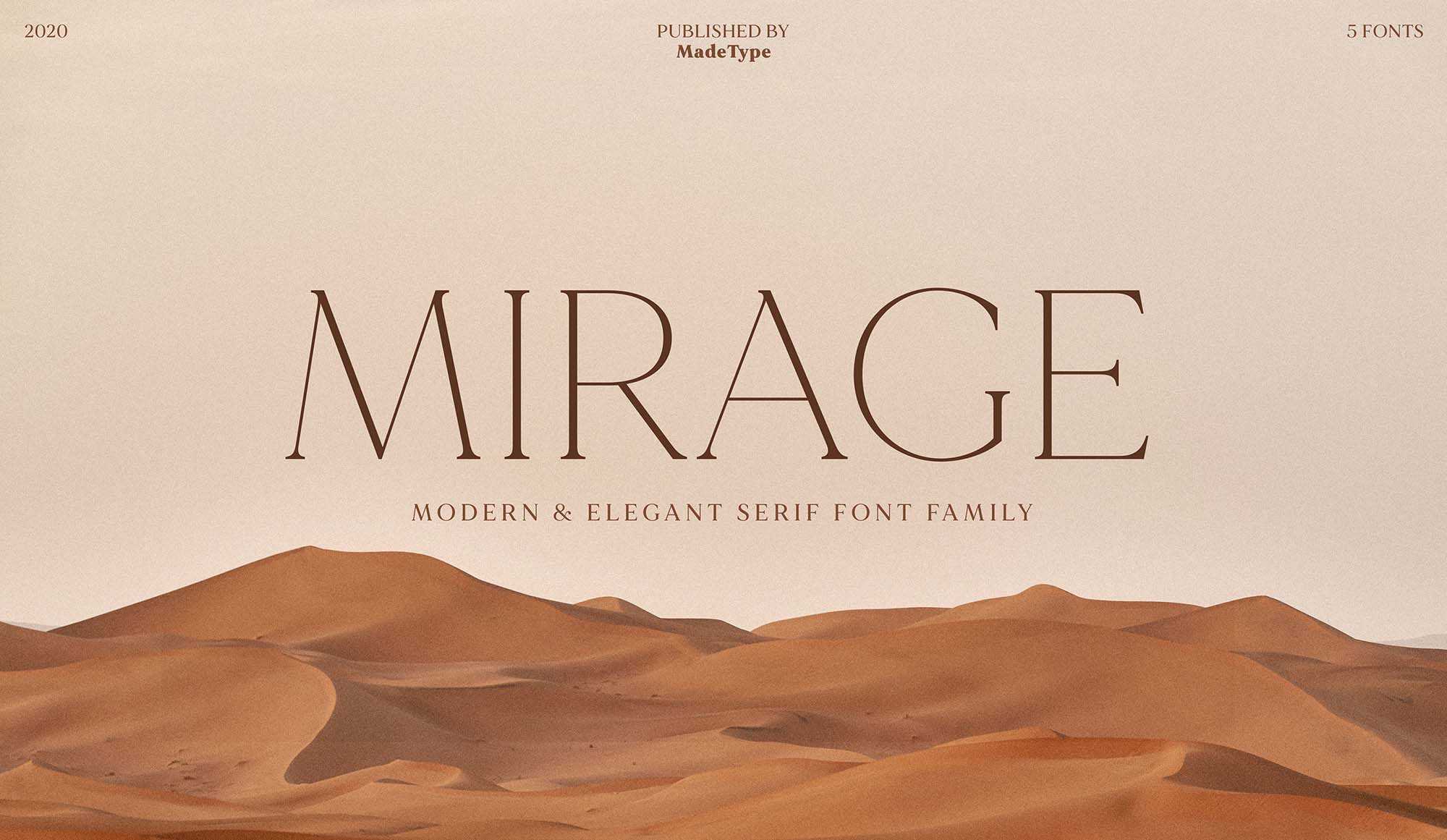
A ideia de uma miragem é algo fascinante mesmo quando sabemos que ela é uma ilusão. Assim como a marionete de uma miragem, o Made Mirage Serif Font oferece uma ilusão de grande beleza e elegância que se dissolve em uma escrita clássica. Ainda que possa ser obtido facilmente, não diminui sua importância. A equipe da Made Type é entusiasmada em compartilhar com você a Made Mirage, uma família de fontes serif modernas. Aproveite esse recurso gráfico, pois não há como escapar da sua beleza e do seu profundo valor.